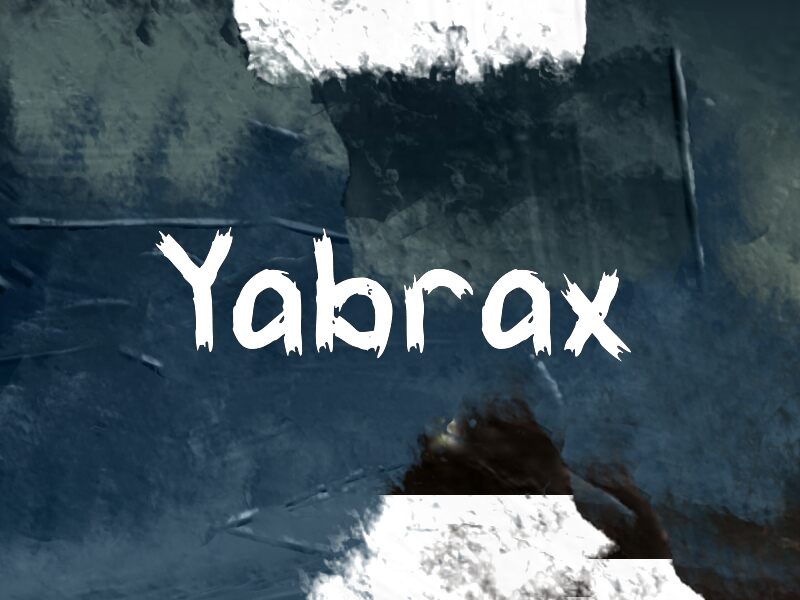
Yabrax
Yabrax, realizzata da Wep, è un font brush gratuito dal carattere ruvido. Con il suo aspetto grezzo, dipinto a mano, richiama più l'estetica dei poster di strada che quella di una calligrafia elegante. Le lettere sembrano trascinate e tamponate con un pennello carico, caratterizzate da bordi irregolari, tratti verticali decisi e forme arrotondate che rendono la texture vivida e protagonista.
Si adatta perfettamente a zine, copertine di album, titoli per film indie, poster e grafiche per abbigliamento, laddove serva un font gratuito capace di sprigionare un'energia scompigliata senza scadere nei cliché del graffiti. Usalo per brevi testi di branding, titoli di copertina o grafiche social d'impatto, quando vuoi che sia la pennellata stessa a parlare.